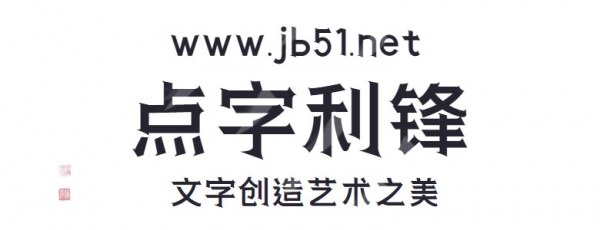
點字利鋒是由點字庫推出的藝術(shù)字體,字體以粗宋風格為主,字體整體比較方正,筆畫粗細均勻,適合應用于藝術(shù)設計、各類廣告和產(chǎn)品包裝設計等領域。
字體以粗宋風格為主,在筆畫的起筆、收筆以及轉(zhuǎn)折處加入相對鋒利、夸張的造型變化,字體整體比較方正,筆畫粗細均勻,視覺效果統(tǒng)一,字體穩(wěn)重,用在內(nèi)文以及標題均可。